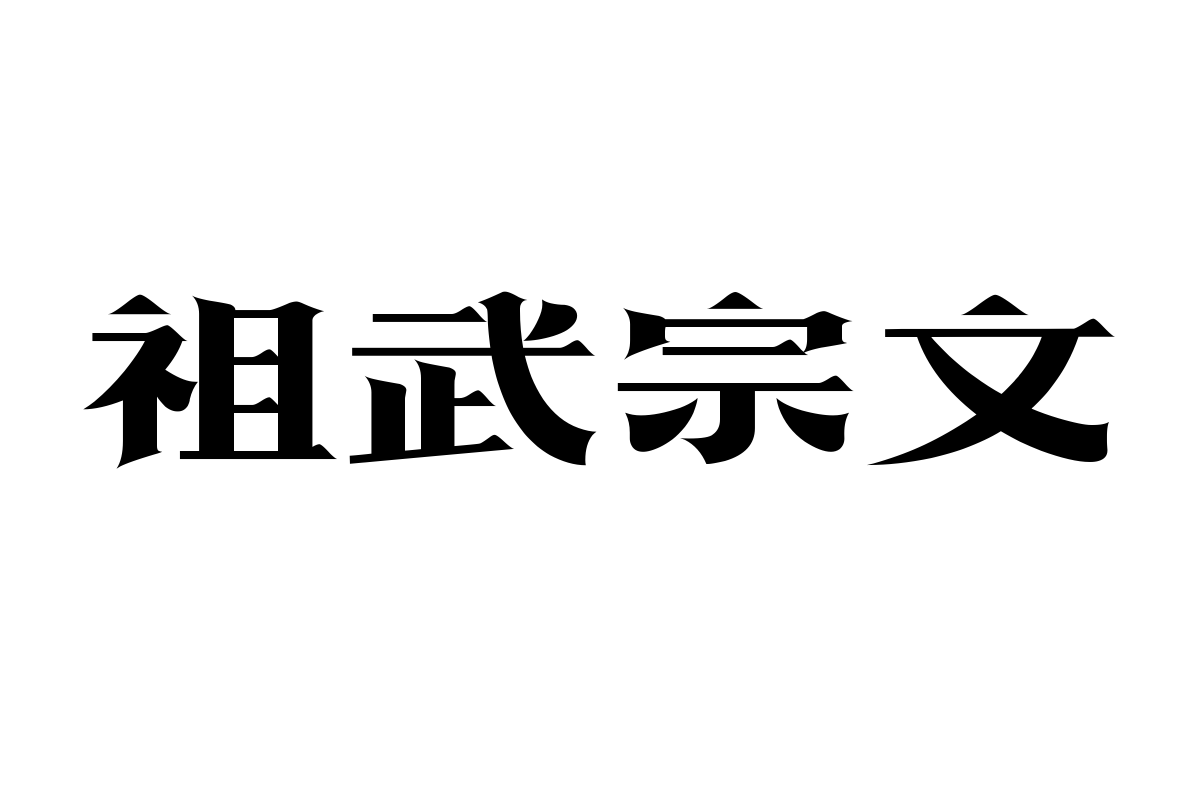
上首墨宋体是一款具有独特风格的中文字体,它结合了传统书法的韵味和现代设计的理念。该字体以其优美的线条、独特的字形结构和丰富的表现力而受到广泛欢迎。
上首墨宋体的特点包括:
1. 字形结构:该字体的字形结构独特,笔画流畅自然,呈现出一种优雅的气质。其字形结构既有传统的韵味,又不失现代感,适合用于各种设计场景。
2. 笔画风格:该字体的笔画风格独特,线条粗细适中,既显得有力又不失柔美。这种风格使得字体在视觉上具有很强的冲击力,能够吸引人们的注意力。
3. 字间距与行距:上首墨宋体的字间距和行距设计合理,既保证了文字的可读性,又增加了设计的美感。这使得该字体在印刷和电子屏幕上都表现出色。
4. 适用场景:上首墨宋体适用于各种设计场景,如广告、海报、书籍、杂志等。它的使用可以使设计作品更加独特和引人注目。
总之,上首墨宋体是一款具有独特风格的中文字体,它结合了传统书法的韵味和现代设计的理念,为设计师提供了丰富的创作灵感。